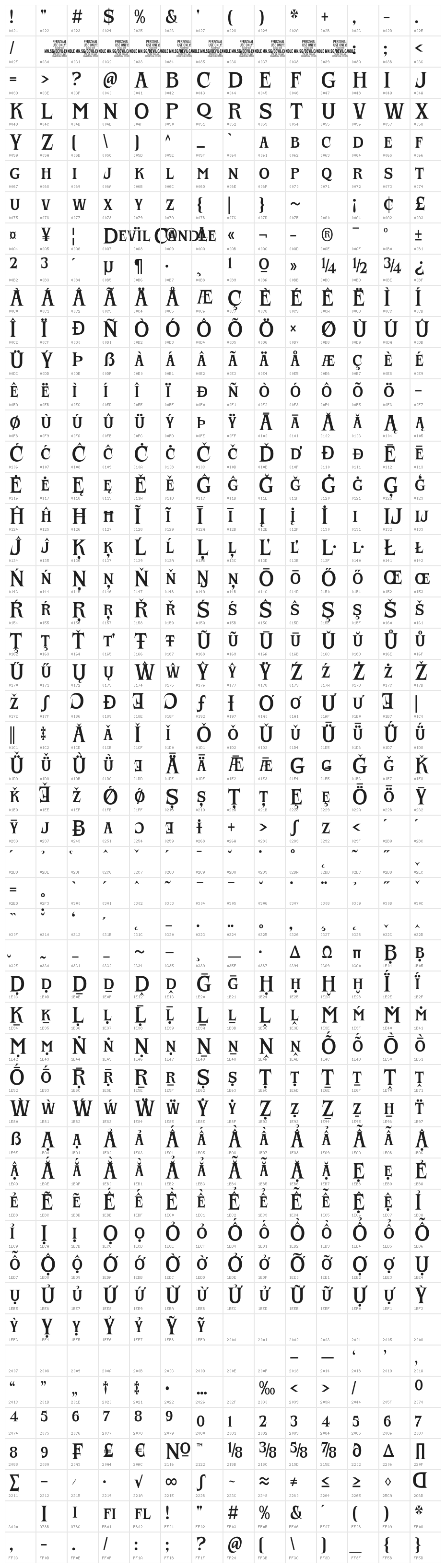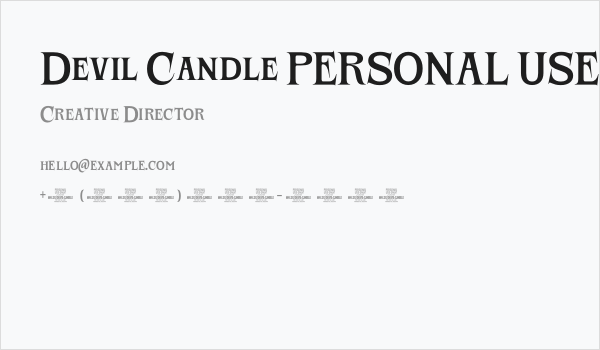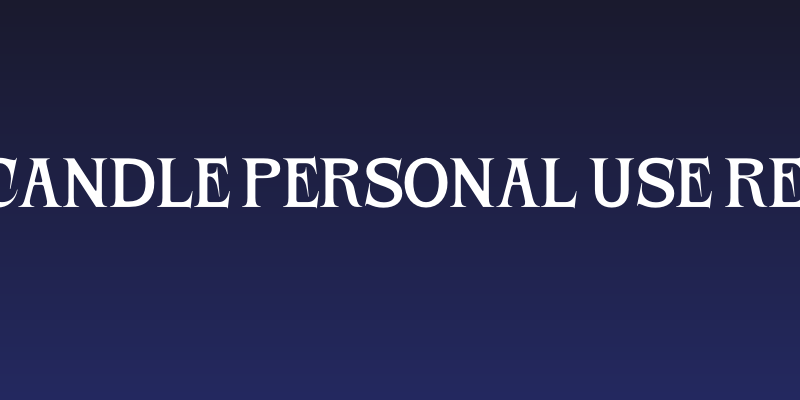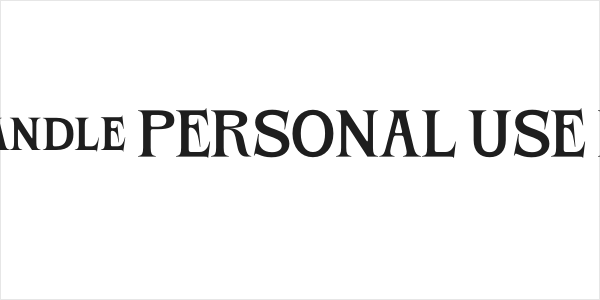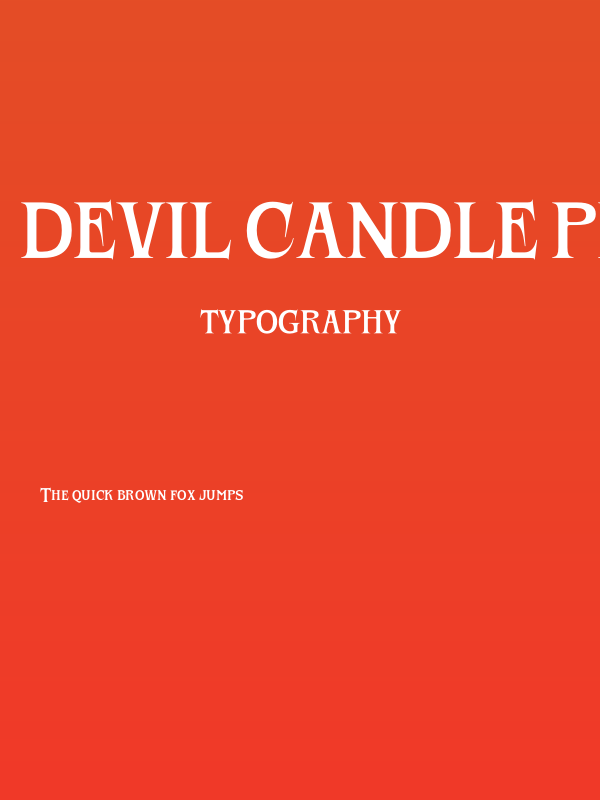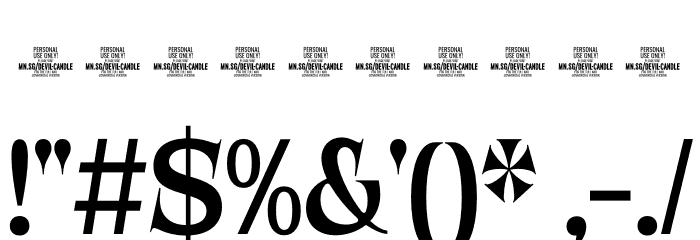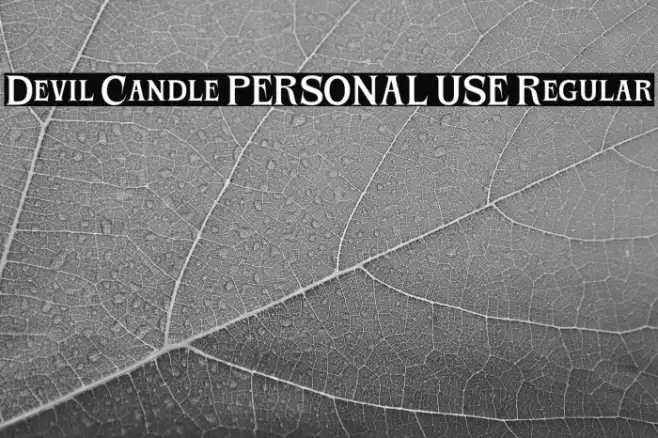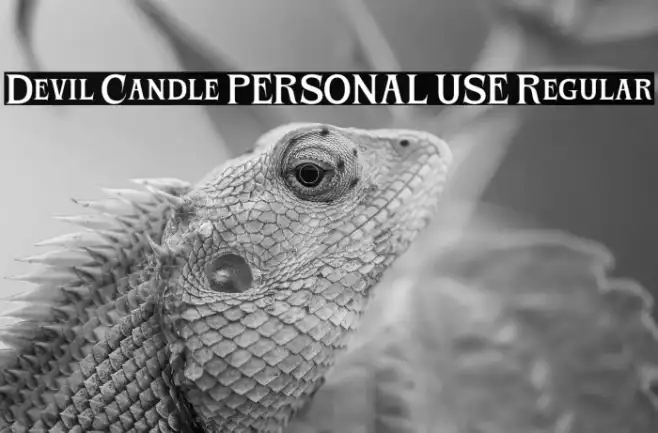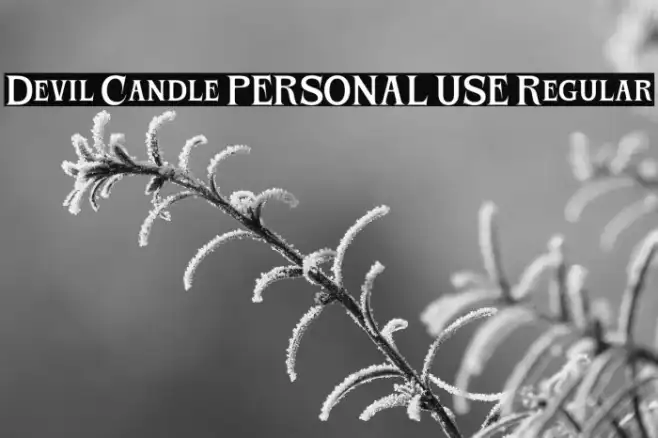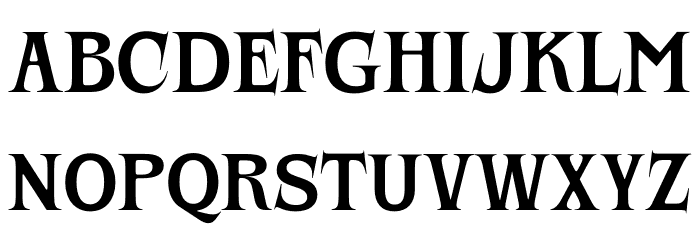
Devil Candle PERSONAL USE Regular Font
✎ Thick
| Vorgeschlagene Projekte | Ideal for posters, album covers, branding, and any project needing a dramatic flair. |